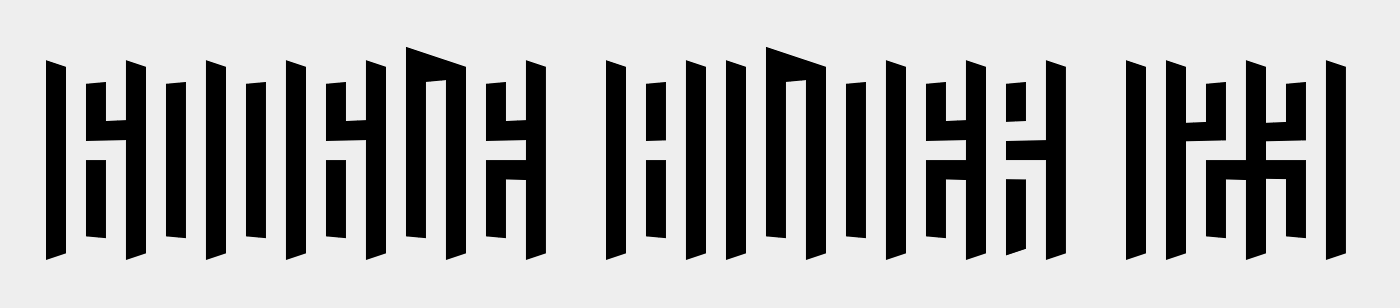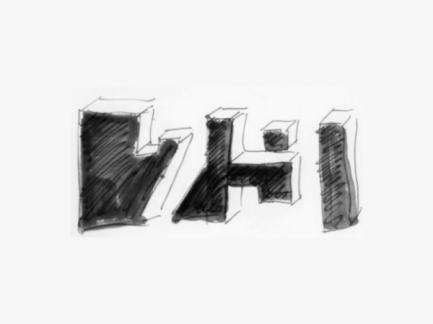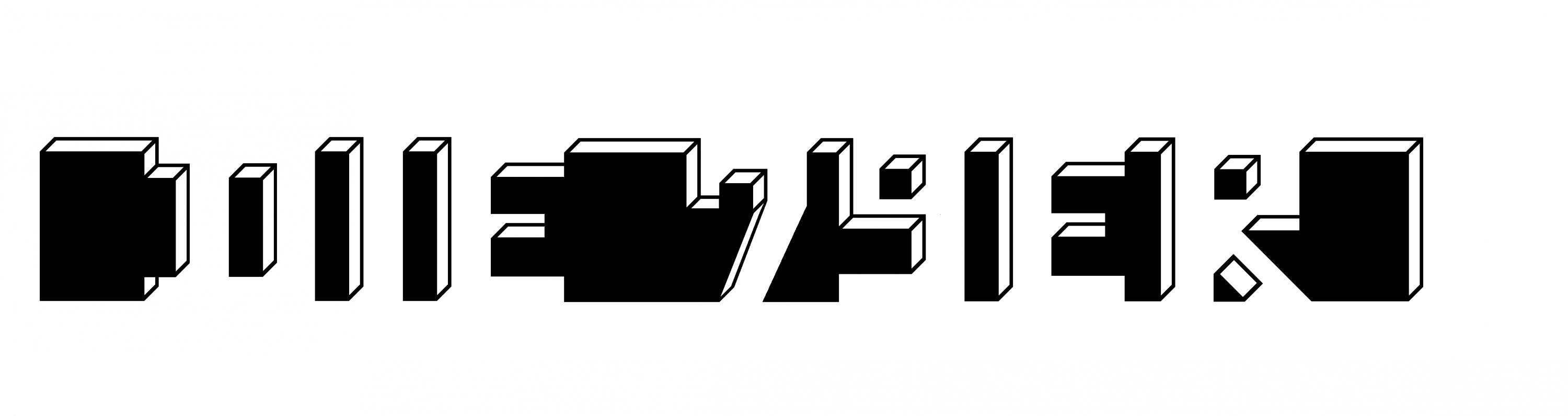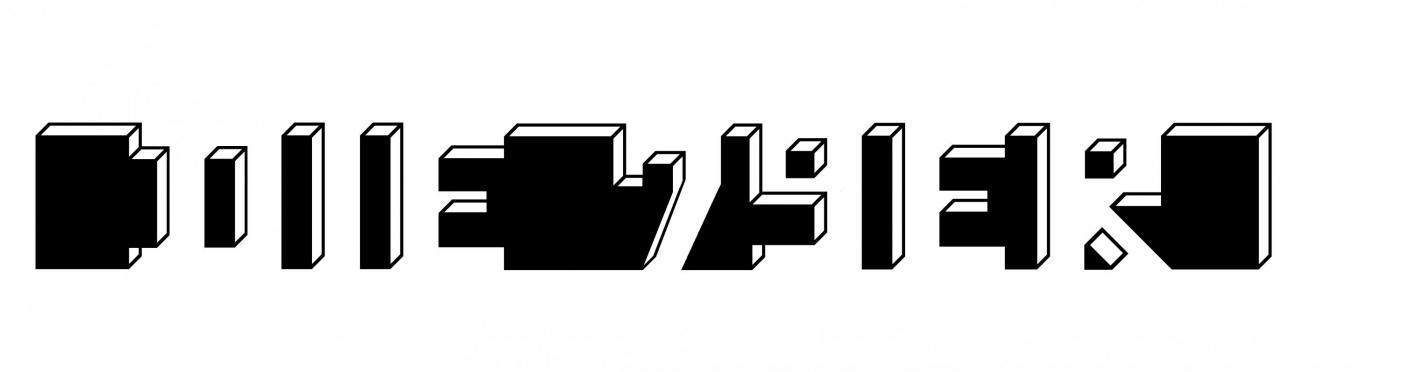
Schriftarterkennung "Sehtest"
Es wäre nett von euch, wenn ihr mir bei der Bestimmung der Schriftart helfen könntet, die auf der Grafik im Anhang verwendet wurde.
Dabei handelt es sich mehr oder weniger um Letter für einen spaßigen "Sehtest".
Falls es sich nicht um einen Font handelt, wäre ich dankbar für das Aufzeigen von Quellen, aus denen man das Alphabet samt Ziffern schöpfen kann.
Kommt dem Gesuchten schon sehr nahe, finde ich.
Leider lassen sich mit diesem Font keine Ziffern darstellen.
Gibt es Alternativen?
Leider habe ich keine Alternativen gefunden.
Ich könnte dir aber etwas mit dieser Schrift setzen und die Zahlen dazu "erfinden".
Oder du fragst @catfonts (unser Spezialist was das Erstellen neuer Fonts angeht) ob er dir einen Font mit Ziffern basierend auf deinem Beispiel und The Namofont erstellt. :-?
Was ich noch gefunden habe ist die QBIG. Die entspricht zwar nicht deiner gesuchten Schrift, würde (meiner Meinung nach) aber trotzdem den Zweck als Sehtest* erfüllen :-):
* OK, vielleicht doch nicht ganz so gut, aber es wäre immerhin eine Alternative mit Ziffern ;-).
Die Janus ist auch nicht schlecht (ist aber nicht 3D):
Für Erfindungen deinerseits wäre ich dankbar.
Ich bräuchte lediglich die Ziffern "7" und "9" für den Schriftzug  "Die 79er".
Hast Du bitte einen Tipp für mich zum Erstellen der Ziffern.
Ich muss und will lernen.:!:
:tutor: Also, @jwqlb, fangen wir an...
Bei den Zahlen habe ich es so gemacht, dass ich mir sie erstmal auf Papier aufgezeichnet, eingescannt und dann in Illustrator vektorisiert habe. Anschließend habe ich die anderen Buchstaben in der Namofont geschrieben, passend skaliert und ein wenig angepasst an den Buchstaben-Zahl-Übergängen. Fertig!
Edit: So sieht übrigens meine Skizze aus (quick and dirty :-D):
Puh, doch schon ganz schön komliziert, die Materie.
So, jetzt habe ich den Schriftzug noch ein wenig pixeltechnisch "aufgebrezelt".
In naher Zukunft werde ich mich dann doch mal mit Adobe Illustrator beschäftigen müssen (Horror),
um solcherart Grafiken als Vektordatei erstellen zu können.
Neue Runde - neues Glück.
Kann mir bitte jemand bei der Identifizierung eines weiteren Fonts helfen?
Meine Recherchen, unter anderem mit der Phrase "font outline strokes", brachte leider nicht den gewünschten Erfolg.
Bei der 9 fehlt unten links etwas.
Oh, ja, stimmt.
Danke für den Hinweis.
Dafür habe ich jetzt bei der 7 etwas weggelassen.
Was meinst Du dazu?
Sieht besser aus! Du lernst schnell, @jwqlb :nicken:.
Das ist mir auch erst jetzt aufgefallen, wo du es erwähnt hast ;-).